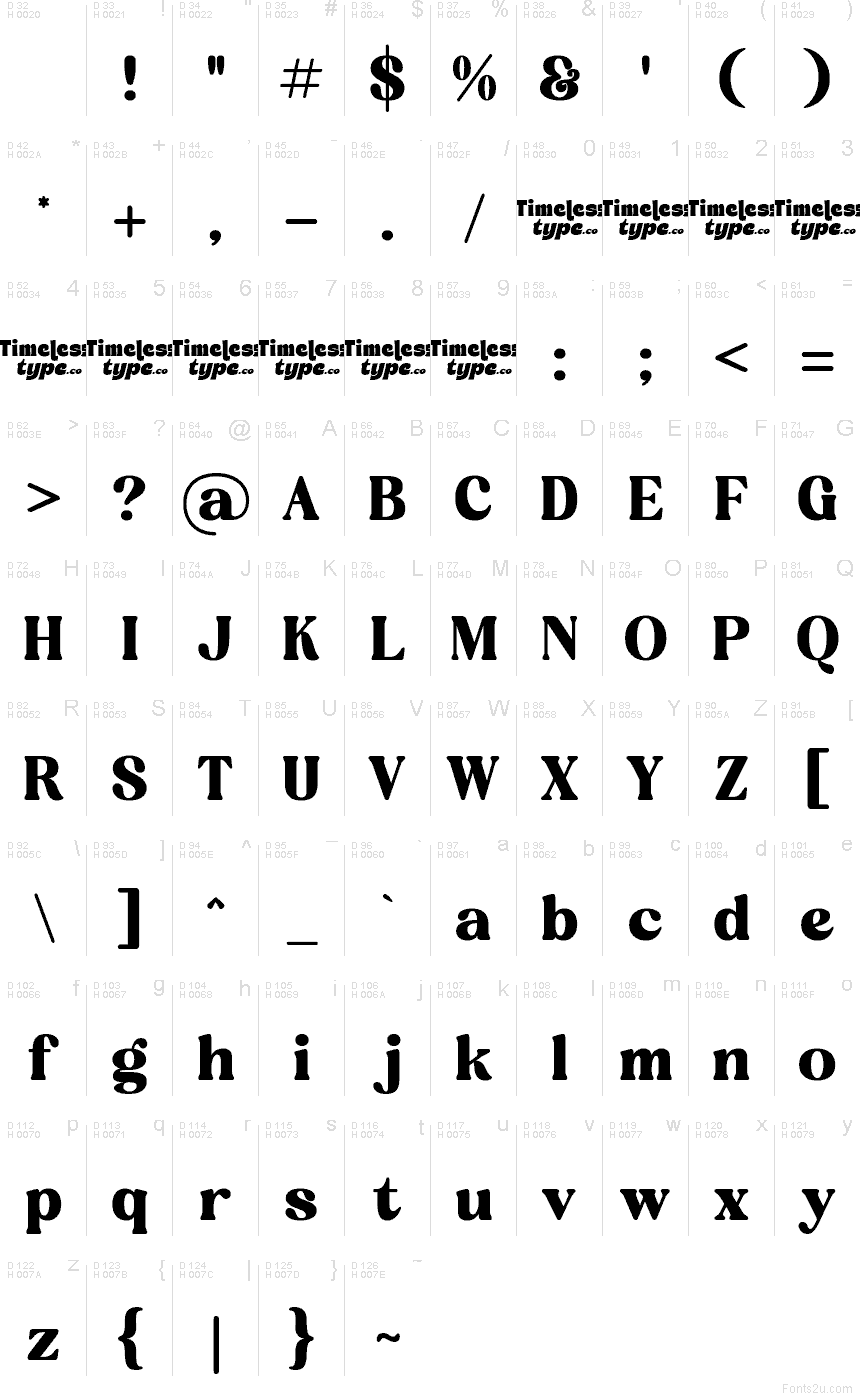
Verleihen Sie Ihren Designprojekten einen Hauch von nostalgischer Raffinesse und zeitlosem Charme. Brighters Peaceful - Classy Retro Serif Font fängt das Wesen der Retro-Ästhetik ein und bewahrt zugleich eine klare, moderne und professionelle Note. Ihre kräftigen, fließenden Züge und eleganten Kurven wecken das Flair der 70er-Jahre – ein unverzichtbares Werkzeug für Designer, die ihren Arbeiten von Vintage inspirierte Eleganz und eine kontrastreiche Silhouette verleihen möchten.
Präzision trifft auf Verspieltheit in dieser außergewöhnlich vielseitigen Schrift, die für ausdrucksstarkes visuelles Storytelling geschaffen wurde. Brighters Peaceful - Classy Retro Serif Font ist die perfekte Wahl für Luxus-Branding, hochwertige Verpackungen und redaktionelle Layouts, die Aufmerksamkeit fordern. Ob Sie ein unverwechselbares Logo, Titelzeilen für Lifestyle-Magazine oder markante Social-Media-Grafiken gestalten: Diese Schrift bietet das visuelle Gewicht und das künstlerische Gespür, das Ihre Marke auf einem wettbewerbsintensiven Markt hervorhebt.
Erschließen Sie globales Potenzial mit fortschrittlichen typografischen Funktionen, darunter 69 Ligaturen und 26 Alternativzeichen, die unendliche Anpassungsmöglichkeiten eröffnen. Dank ihrer umfassenden Mehrsprachenunterstützung fügt sich Brighters Peaceful - Classy Retro Serif Font nahtlos in weltweite Märkte ein und erweist sich als unglaublich vielseitig für internationale Projekte. Diese professionellen Funktionen ermöglichen es Kreativen, typografische Konsistenz zu wahren und gleichzeitig einzigartige Zeichenkombinationen für eine maßgeschneiderte visuelle Identität zu erkunden.
Definieren Sie Ihre kreative Identität neu – mit einer Schrift, die ausdrucksstarke Persönlichkeit und geschäftliches Prestige meisterhaft ausbalanciert. Brighters Peaceful - Classy Retro Serif Font ist nicht bloß eine Schriftart, sondern eine strategische Bereicherung für alle Gestalter, die Wärme und Luxus gleichermaßen vermitteln möchten. Die Einbindung dieser erstklassigen Serifenschrift in Ihr Design-Toolkit stellt sicher, dass Ihre Marke zeitlos und einprägsam bleibt und über sämtliche Print- und digitalen Plattformen hinweg eine anspruchsvolle Ästhetik ausstrahlt.